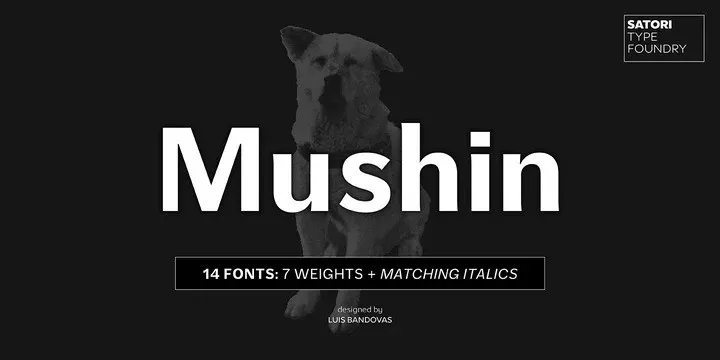
Mushin Sans Serif Font
A Mushin Sans Serif é uma família tipográfica de tipo sem serif inspirada nas formas humanísticas do século XX, mas que traz também características grotescas, um pouco no estilo dos inícios da década de 1900. Com seu conjunto de 14 fonts, incluindo as versões romanas e suas itálicas perfeitamente complementares, a fonte Mushin traz o charme das formas humanísticas junto com uma pitada de modernidade grotesca. Esta família tipográfica é ideal para projetos que buscam equilibrar clareza de leitura com um toque de inovação e personalização única, seja em materiais impressos ou digitalmente. Seja você designer gráfico, publicitário ou webmaster, a Mushin Sans Serif oferece o conjunto perfeito de fontes para destacar seu trabalho de uma maneira que se adapta à dinâmica dos tempos modernos, mantendo-se fiel aos fundamentos do design tipográfico clássicos.